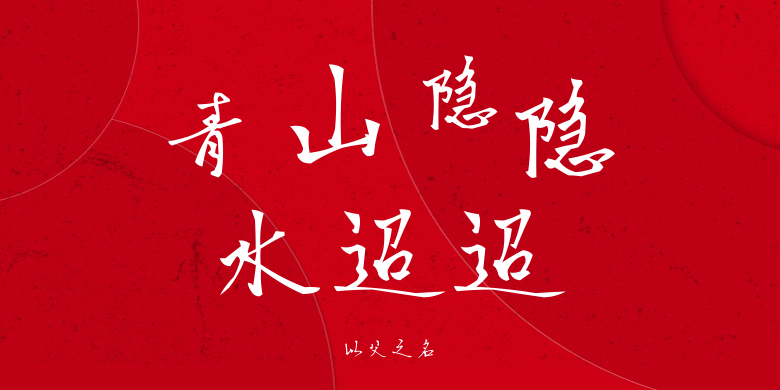
以父之名
以父之名,这款字体结构工整、笔画清晰,兼顾美观与易读性,适用于标题、正文、海报、包装、LOGO 等多种场景。字形优雅稳定,风格百搭耐看,适配日常排版与创意设计,让文字呈现更舒适、更具质感。以父之名一笔一画,皆是细节,以均衡的比例、流畅的线条打造舒适视觉体验,字形端正大气,风格简约现代。无论是商业设计、品牌宣传还是日常排版,都能轻松驾驭,让文字更有格调与力量。以父之名字体下载。